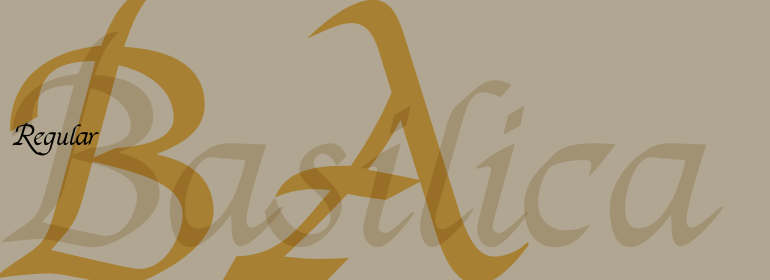
Basilica
Basilica,这款字体结构工整、笔画清晰,兼顾美观与易读性,适用于标题、正文、海报、包装、LOGO 等多种场景。字形优雅稳定,风格百搭耐看,适配日常排版与创意设计,让文字呈现更舒适、更具质感。Basilica一笔一画,皆是细节,以均衡的比例、流畅的线条打造舒适视觉体验,字形端正大气,风格简约现代。无论是商业设计、品牌宣传还是日常排版,都能轻松驾驭,让文字更有格调与力量。Basilica字体下载。